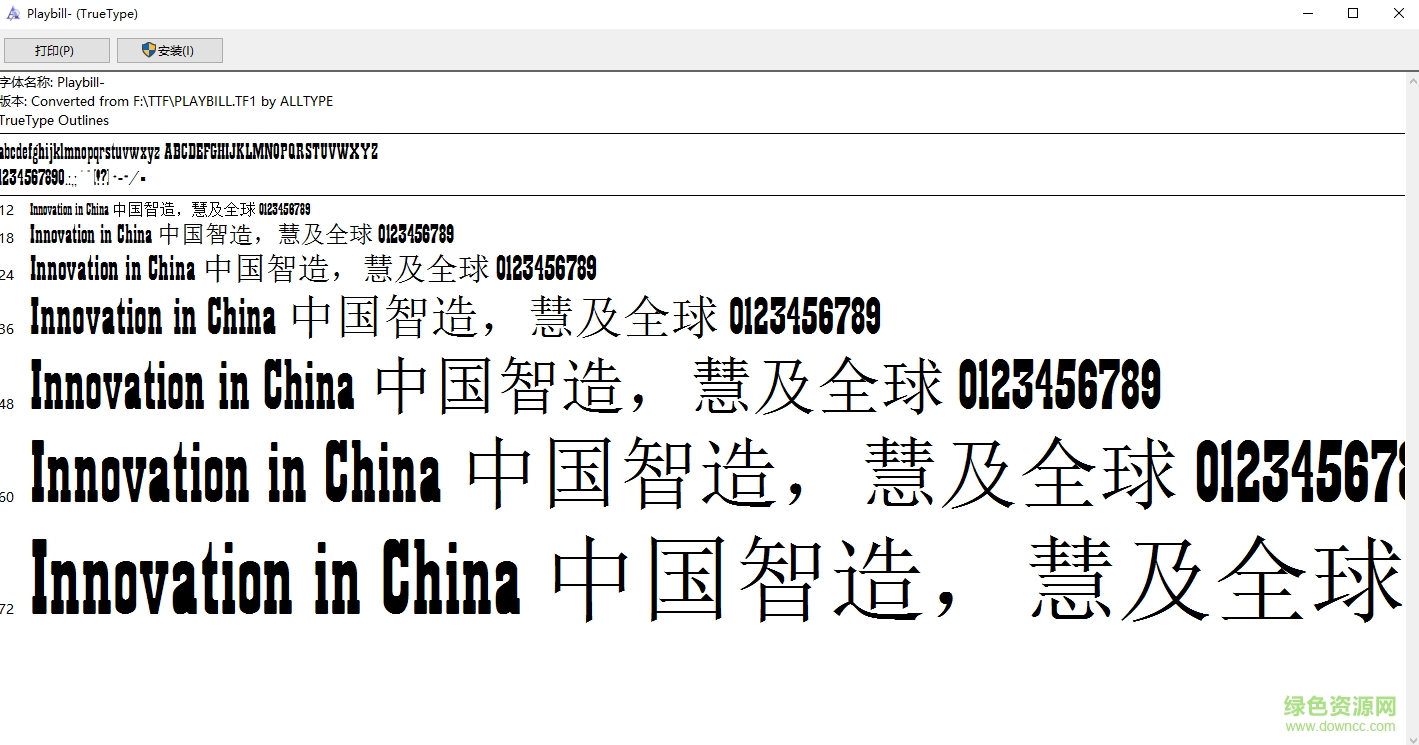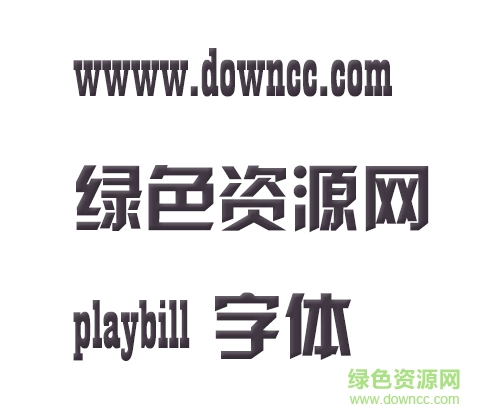
playbill 字體免費版
playbill字體是一款最新的英文字體,字體規(guī)整漂亮,歡迎喜歡的用戶來綠色資源網(wǎng)下載。下文附有安裝教程,歡迎仔細閱讀。
playbill字體介紹
playbill字體是一款用于標題設(shè)計方面的字體
playbill字體
playbill字體點評
字體雋秀工整,結(jié)構(gòu)狹長,字間距較大,排印清晰,整齊劃一,適用于書籍、報刊、雜志的標題字。規(guī)則中正而有動態(tài),頗具審美價值。